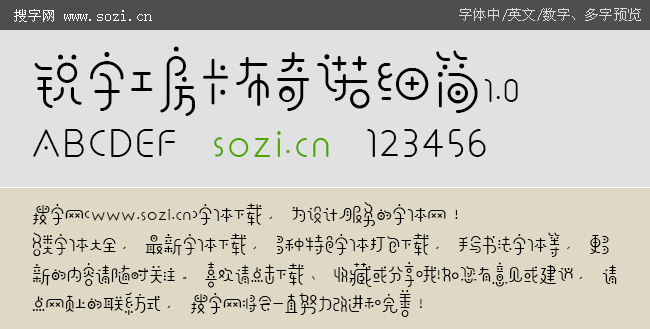
銳字工房卡布奇諾細(xì)簡(jiǎn)
搜字網(wǎng)提供一款非常藝術(shù)的銳字工房卡布奇諾細(xì)簡(jiǎn)下載銳字工房卡布奇諾細(xì)簡(jiǎn)是一款字形呈卡通效果的銳字工房字體,該字體極具藝術(shù)感,非常有趣,適用于包裝印刷、廣告設(shè)計(jì)、平面設(shè)計(jì)、兒童產(chǎn)品等領(lǐng)域。